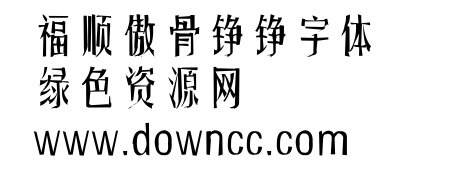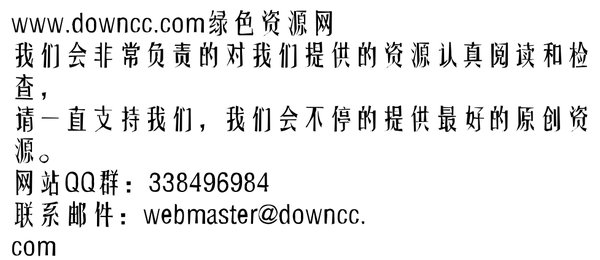
福順傲骨錚錚
福順傲骨錚錚字體福順字體洗了一款彰顯整齊的藝術(shù)字體,文筆端正不阿、字跡清秀大方,給人清晰簡(jiǎn)約的視覺(jué)好感,如果你也喜歡,請(qǐng)來(lái)綠色資源網(wǎng)試試吧!
福順傲骨錚錚體特色
傲骨錚錚是指高傲不屈的性格。比喻剛正、堅(jiān)貞。
福順傲骨錚錚字體給你十分端莊嚴(yán)謹(jǐn)?shù)目犊畾猓o你正氣凝然的視覺(jué)效果,可以廣泛運(yùn)用于平面設(shè)計(jì)、海報(bào)設(shè)計(jì)、排版印刷等多種場(chǎng)合。